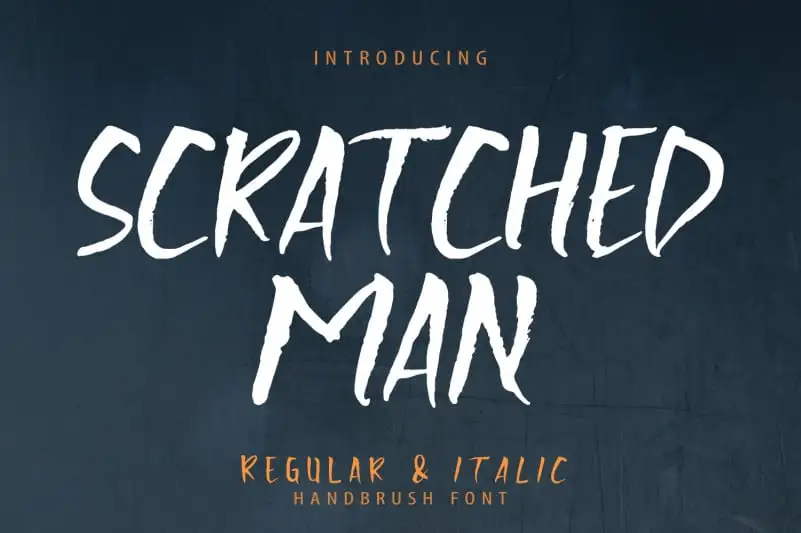
Scratchedman Display Font – Download Grátis
A fonte ‘Scratchedman Display Font’ é uma criação natural e autêntica do OCSstudio, que oferece um estilo de escrita manuscrita robusto para projetos de design. Este tipo mistura letras maiúsculas fortes para destacar-se em seu trabalho gráfico. A fonte Scratchedman tem dois estilos: Regular e Italic, permitindo a personalização dos seus projetos de design. Além disso, Suporte multilíngue é outro ponto forte desta fonte. Ela é ideal tanto para designer profissional quanto para aqueles que querem dar um toque único em seu próximo projeto gráfico. OSCRstudio criou uma fonte versátil e autêntica perfeita para designers digitais.